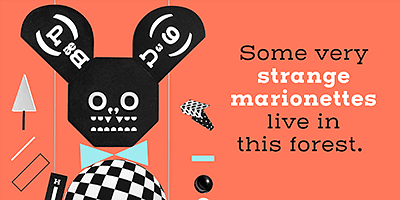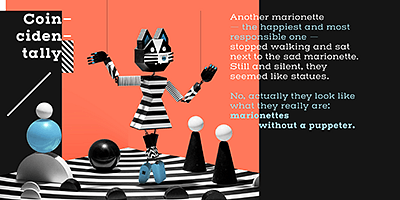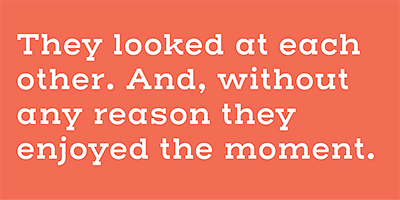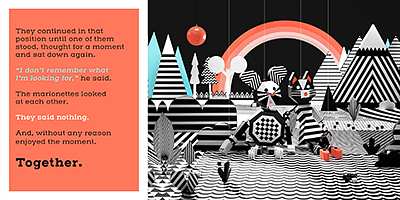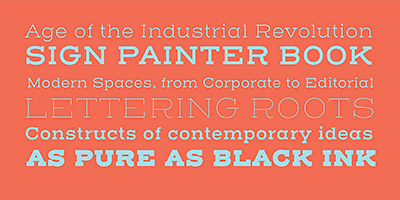
Unas cuantas mayúsculas en negrita dibujadas por Albert Du Bois para el libro de 1906 Henderson Sign Painter me llevaron a ver cómo los pintores de carteles se acercaron a las slabs después de la revolución industrial. A partir de ahí, sucedió lo de siempre. Mi ejercicio en las primeras raíces de las letras de lo que eventualmente se convirtió en la definición de tipografía geométrica terminó teniendo vida propia. Las mayúsculas llevaron a las minúsculas, un grosor idiosincrásico en negrita llevó a seis más, y los verticales llevaron a la cursiva. Lo que era poco interesante a principios del siglo XX, me persuadió para hacerlo lo suficientemente interesante un siglo después.